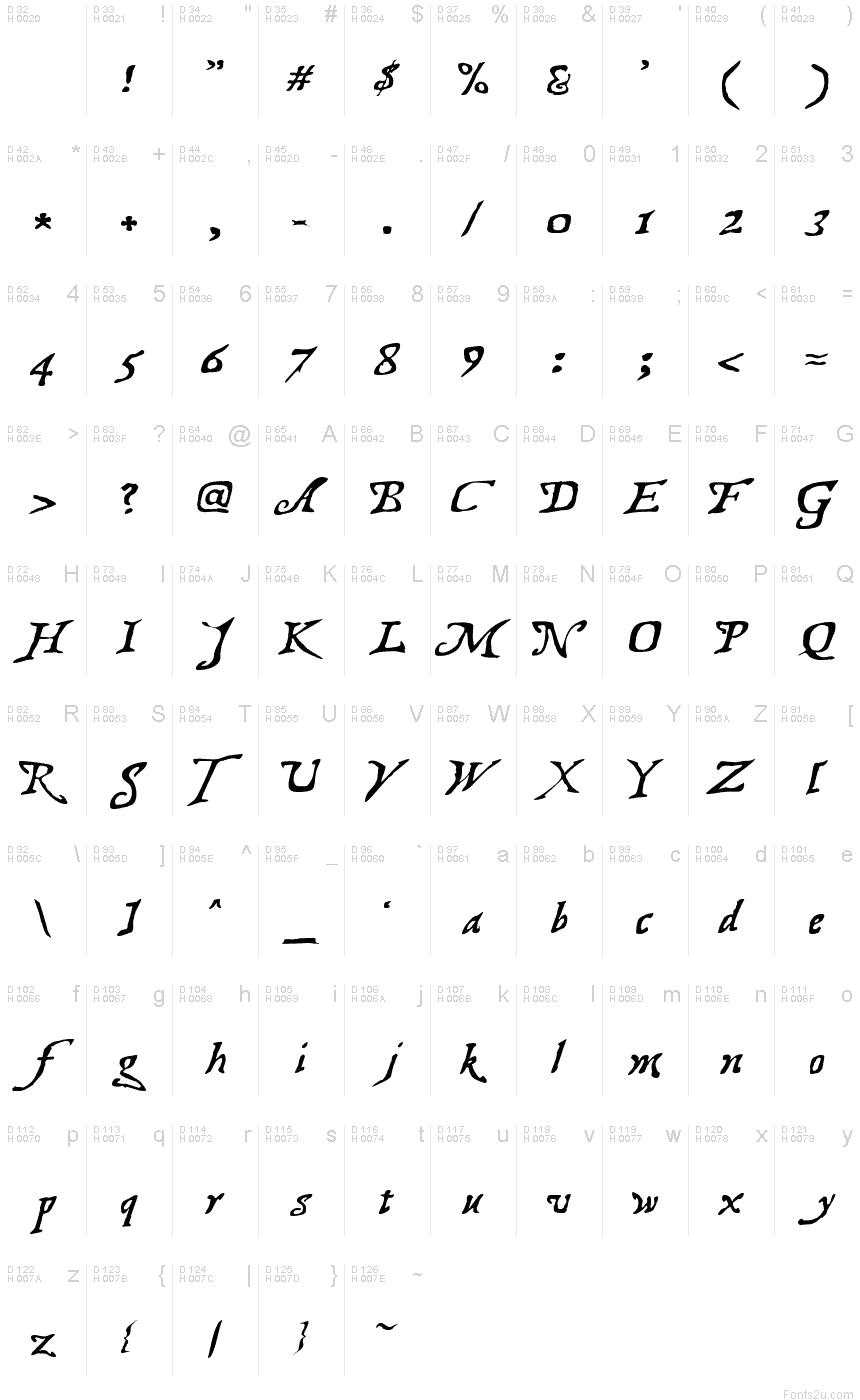
Treasure Map Deadhand od GemFonts & Phoenix Phonts to darmowy, odręczny krój pisma, który przywołuje klimat starych, wyblakłych map. Litery pochylają się i wiją dzięki swobodnym pociągnięciom pędzla, ostrym łączeniom i lekko postrzępionym krawędziom, dzięki czemu font sprawia wrażenie pisanego ręcznie, a nie starannie kreślonego piórem.
Naturalnie pasuje do plakatów w pirackim stylu, okładek książek przygodowych, tytułów gier, zaproszeń i opakowań tematycznych, gdzie ten bezpłatny font o surowym, kaligraficznym charakterze pozwala błyskawicznie nadać właściwy ton. Długie, zakręcone linie świetnie sprawdzają się w krótkich nagłówkach, początkach rozdziałów czy inicjałach, ponieważ krój pisma wnosi wystarczająco dużo dynamiki i wyrazu, nie potrzebując przy tym dużej ilości tekstu.
Treasure Map Deadhand